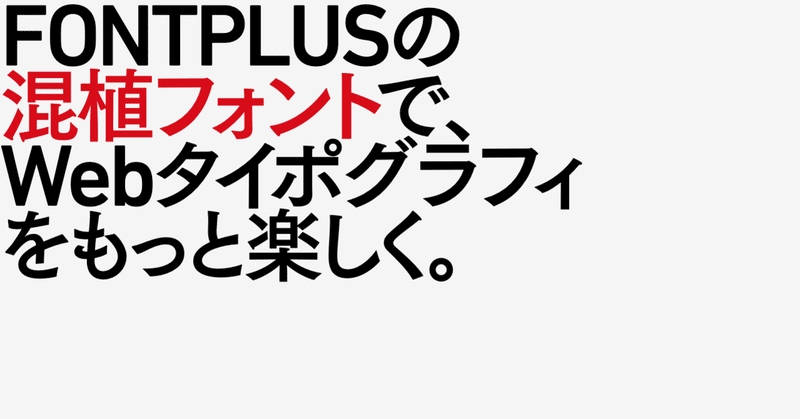
和欧混植をWebフォントで簡単に使える「混植フォント」なら、Webタイポグラフィをもっと楽しめる
FONTPLUSではこのたび、和文フォントと欧文フォントを組み合わせた「混植フォント」の提供を開始しました。この記事ではこの混植フォントをご紹介するとともに、それぞれの書体の魅力をあらためて探ってみたいと思います。
混植フォントとは
ウェブでは和文フォントと欧文フォントをかんたんに組み合わせることが可能です。CSSで以下のように指定すれば、ウェブページ上で筑紫ゴシックとDIN Nextの和欧混植が実現できます。
しかしこのようなCSSによる和欧混植では、和文フォントと欧文フォントそれぞれの文字サイズやベースライン位置を調整することはできません(少なくとも今のところは)。そのため、組み合わせによっては両者がうまく調和せず、ちぐはぐな印象を与えてしまうこともあります。
FONTPLUSの混植フォントはこのような課題を解決すべく生まれました。和文フォントと欧文フォントを組み合わせ、さらに文字サイズやベースライン位置の調整を加え、あらかじめ混植されたWebフォントとしてご提供します。
▲欧文フォントと和文フォントをCSSで組み合わせた場合(上)と、フォントプラスの混植フォントでの表示(下)の比較
CSSでは、このように1つのフォントファミリーを指定するだけで混植フォントが利用できます。
ラインナップのご紹介
それでは、このたびリリースされた混植フォントのラインナップをご紹介します。今回リリースされたのは、ウェブで採用されることの多い日本語ゴシック体と欧文サンセリフ体の組み合わせによる、4ファミリー8書体です。
筑紫ゴシック Pr5 R+Between™ Pro 2 Light
筑紫ゴシック Pro B+Between™ Pro 2 Medium
筑紫ゴシック Pr5 R+Avenir® Next Pro Regular
筑紫ゴシック Pro B+Avenir® Next Pro Medium
筑紫ゴシック Pr5 R+Helvetica® Now Text Light
筑紫ゴシック Pro B+Helvetica® Now Text Medium
筑紫ゴシック Pr5 R+DIN Next™ Pro Light
筑紫ゴシック Pro B+DIN Next™ Pro Medium
ここからは、今回リリースされた混植フォントに含まれている書体について、あらためてその魅力を探ってみたいと思います(FONTPLUSでは、これらの書体は混植フォントとしてだけではなくそれぞれ単独でもご利用いただけます)。
筑紫ゴシック
筑紫ゴシックは、フォントワークスのフラグシップ書体である筑紫書体シリーズ初のゴシック体として、2006年にリリースされました。革新的な筑紫書体を次々に生み出している書体デザイナー藤田重信氏による、柔らかさとしなやかさ、そして緊張感をあわせ持ったデザインは、ほかに類を見ないものです。ゴシック体はときに無機質な印象になってしまうこともありますが、筑紫ゴシックは文字を書く人の手の運動を感じさせるような、ゆたかな表現力を持っています。ウェブページでは本文や見出しはもちろん、ユーザーインターフェースのフォントとして採用しても、美しく、それでいて動きのある画面を実現できるでしょう。
Between 2
Between(ビトウィーン)はモノタイプの小林章氏によるデザインで、2016年にリリースされたばかりの新しい書体です。異なる「フレーバー」を持った3つの書体からファミリーが構成されるという、ユニークな特徴を持っています。モダンでかっちりした印象のBetween 1、オーガニックで親しみやすいBetween 2、そして快活で躍動感あふれるBetween 3。この中から私たちが混植フォントに選んだのは、本文書体としてより自然な読みやすさを持つBetween 2です。筑紫ゴシックとの組み合わせで、今までにない新鮮なフレーバーを味わっていただきたいと思います。
Avenir Next
Avenir(アヴェニール)はUniversやFrutigerなどでも知られるアドリアン・フルティガー氏のデザインにより、1988年にリリースされました。ジオメトリック・サンセリフに分類されますが、幾何学的な純粋さよりも読みやすさを重視した書体として高い評価を得ています。モダンで洗練されていながら、どこか人間味を感じさせる絶妙なデザインです。
私たちが混植フォントのラインナップとして採用したAvenir Next(アヴェニール・ネクスト)は、2004年にライノタイプによって改刻されたバージョンです。デザインが全面的に改善されているほか、ウェイトのバリエーションが増え、より幅広く使える書体になりました。
Helvetica Now
Helvetica(ヘルヴェチカ)はおそらく世界でもっとも有名な書体です。書体にあまり詳しくない方でもその名前は聞いたことがあるのではないでしょうか。デザイナーのマックス・ミーティンガー氏とディレクターのエドアード・ホフマン氏が中心となって開発され、1957年にスイスのハース社からリリースされました(当初はNeue Haas Groteskという名前でした)。それ以来60年以上にわたって、ブランドのロゴや公共のサイン、広告、Tシャツなど、世界中のあらゆる場面で広く使われ、定番書体として不動の地位を築いています。信頼感がありながらも洗練されすぎず、親しみやすさを感じさせるところが人気の秘密でしょうか。
Helvetica Now(ヘルヴェチカ・ナウ)は2019年にリリースされた最新版のHelveticaです。従来のHelveticaは本文で読みやすいとは言えないとされてきましたが、Helvetica Nowでは文字サイズによってデザインの異なるDisplay、Text、Microという3つのスタイルが用意され、可読性が大きく向上しました。フォントプラスでは混植フォントとして本文に適したTextを選び、筑紫ゴシックと組み合わせています。
DIN Next
DIN Next(ディン・ネクスト)は、1930年代にドイツ規格協会(DIN)がドイツの公共書体として制定したDIN 1451をもとに、2009年にモノタイプによって改刻された書体です。DIN 1451の持つ、工業製品を思わせる機械的・幾何学的な印象を保ちながら、角を少し丸めるなどの微妙な視覚調整を加え、人の手に馴染む道具のような感触を獲得しています。ひと目でそれとわかる独特の字形は見出しなど大きなサイズで映えますが、本文に採用してもユニークな印象を与えられるでしょう。